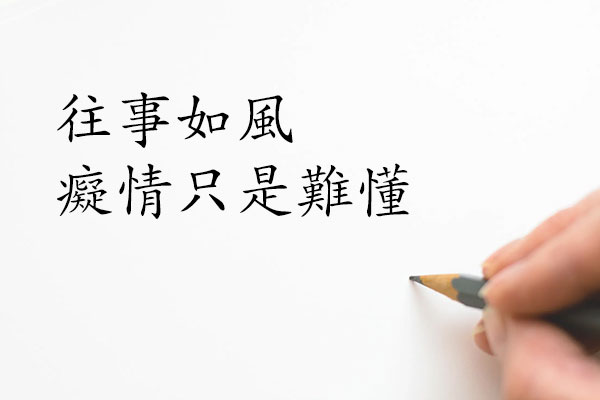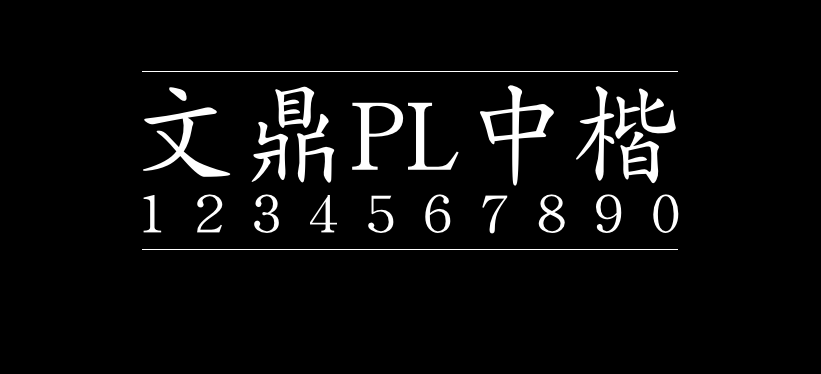
文鼎PL中楷
文鼎PL中楷(AR PL KaitiM Big5)是Linux上最早的高质量开源中文字体,是文鼎科技免费提供给开源社区的4套公众授权字体之一。4套公众授权字型是:文鼎细上海宋、文鼎中楷、文鼎简报宋、文鼎简中楷。这4套公众授权字体在自由软件社区中大受好评,并广泛流传使用。
文鼎PL中楷主要以繁体字形为主,中国大陆的小伙伴如果需要简体可以下载文鼎PL简中楷
字体名称中的“PL”并非指漂亮,而是代表这款字体是公众授权Public License。